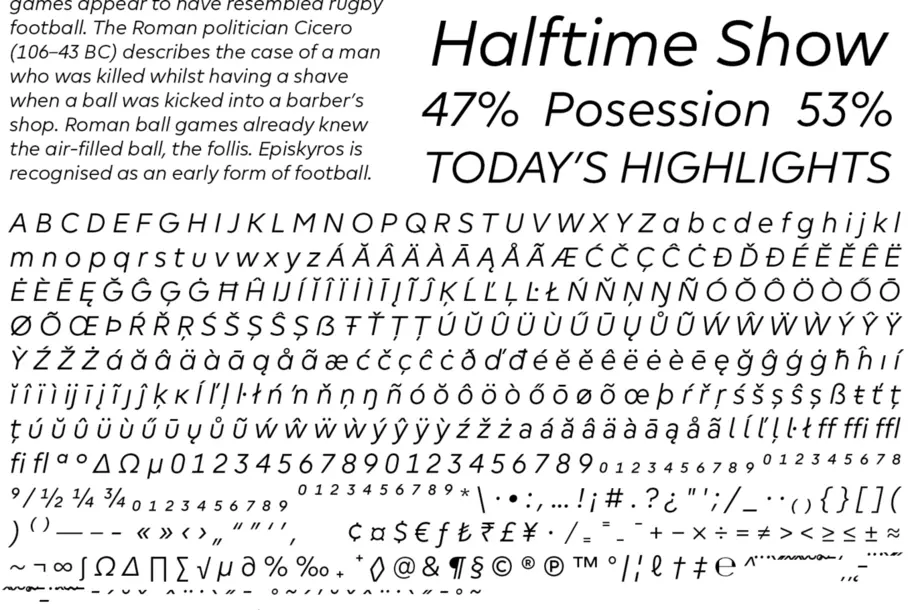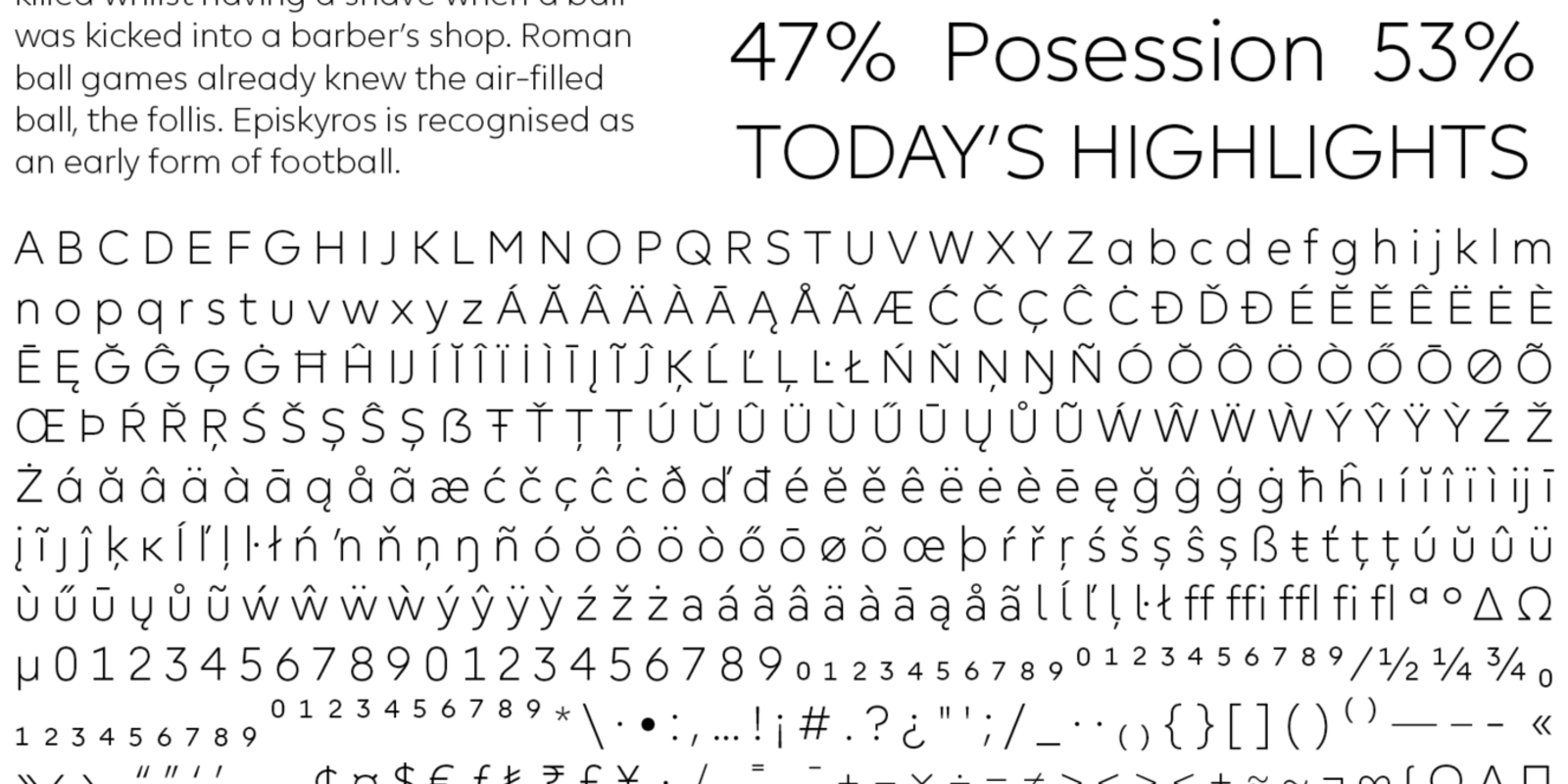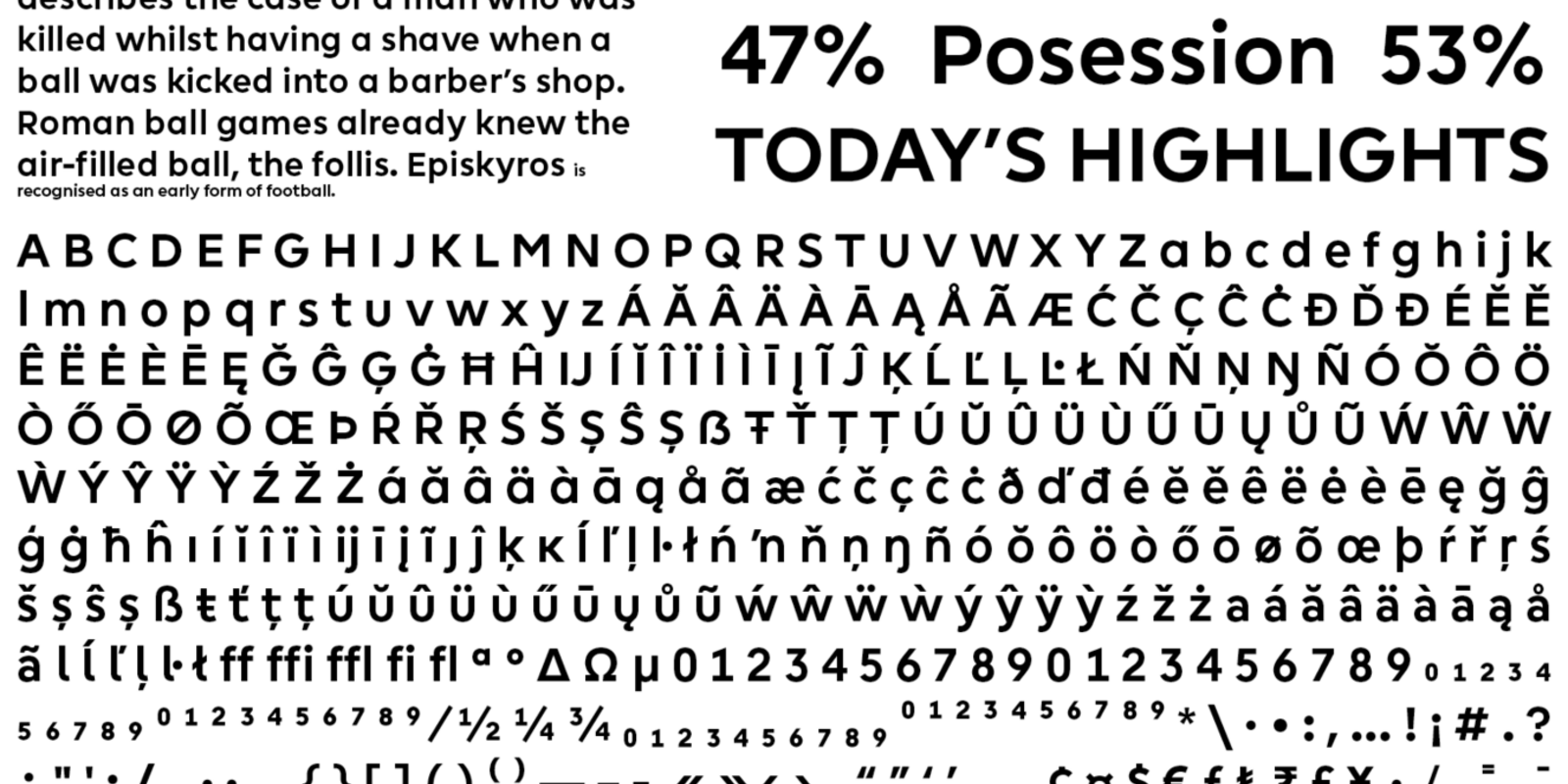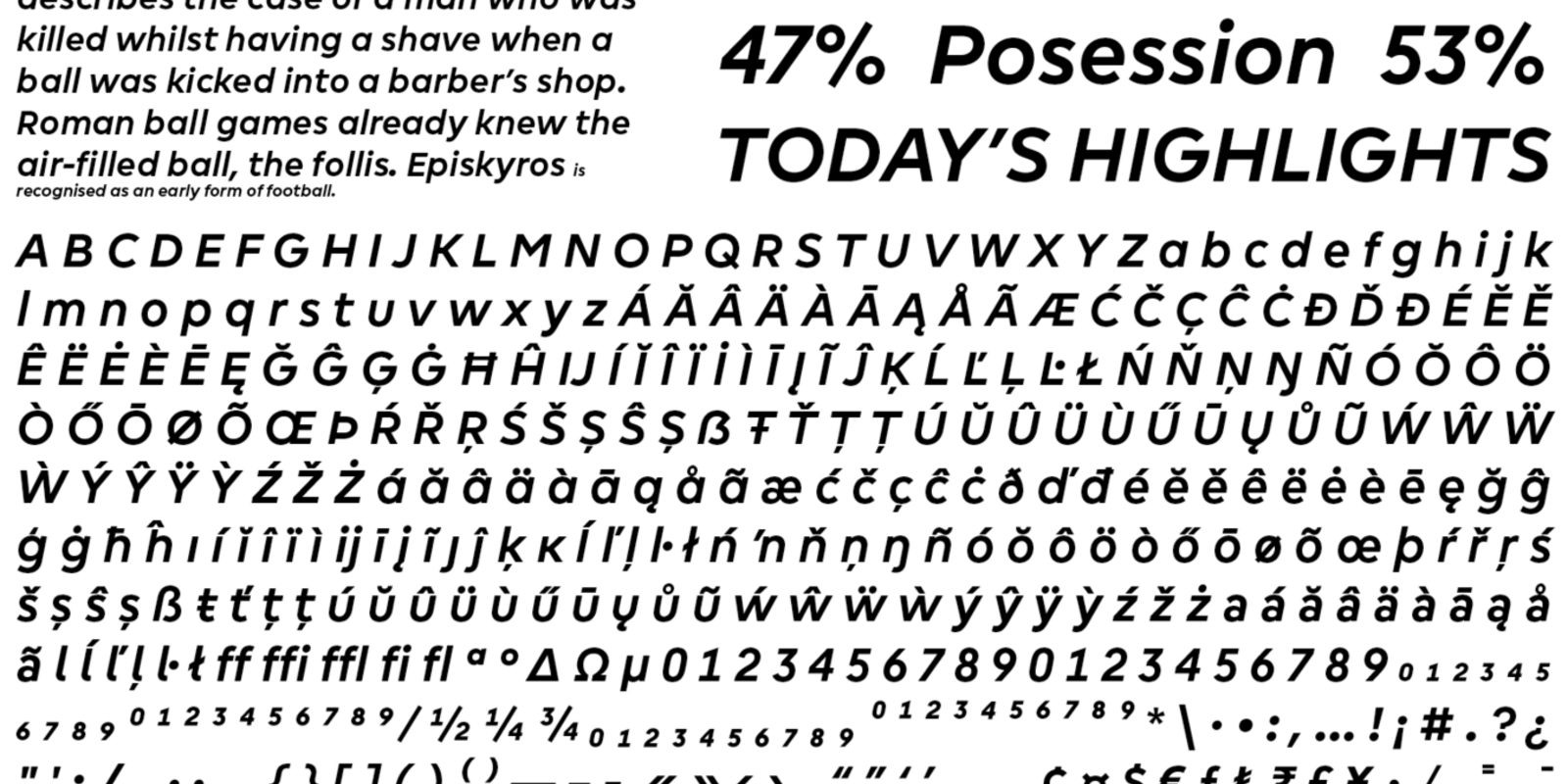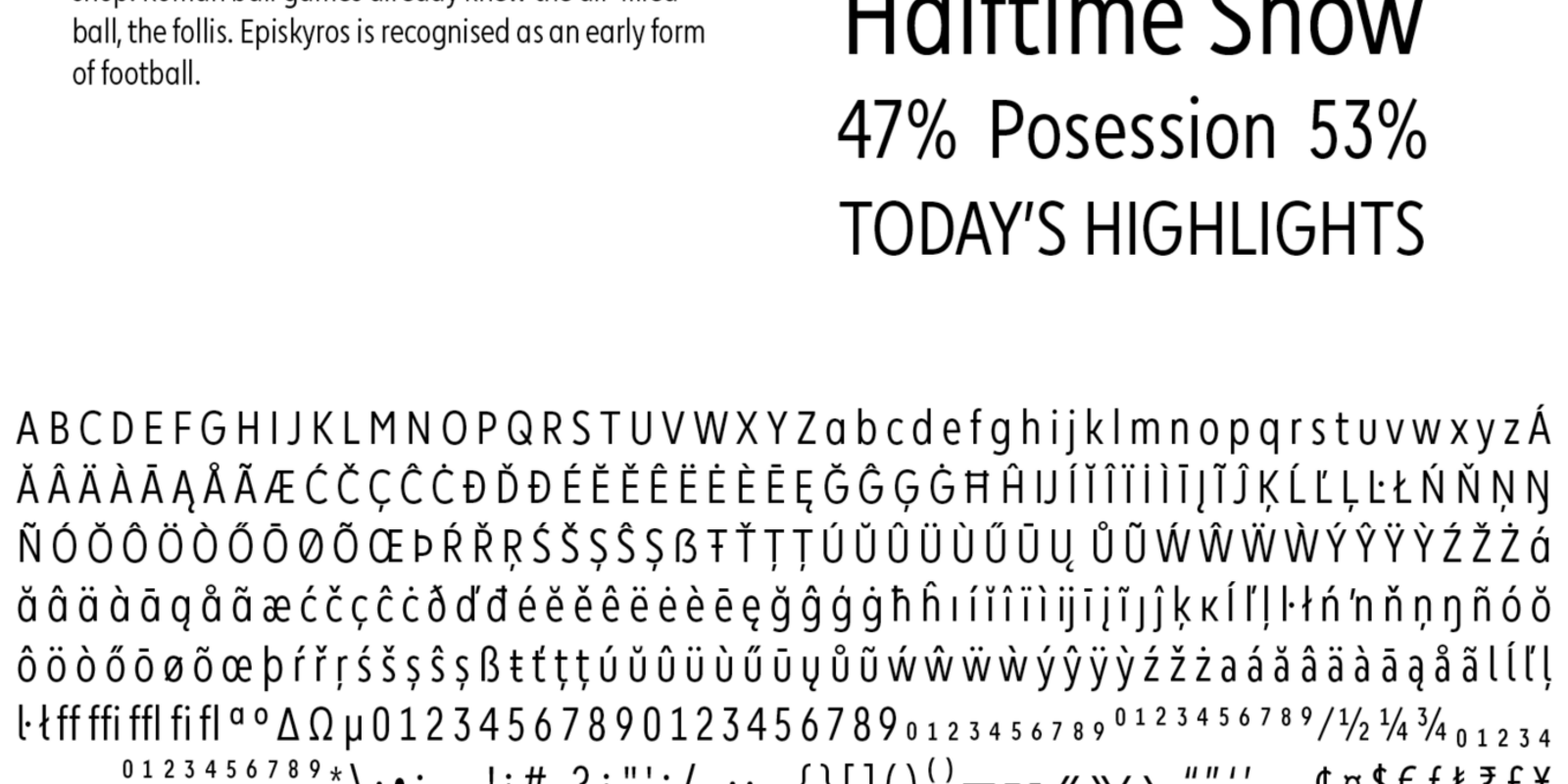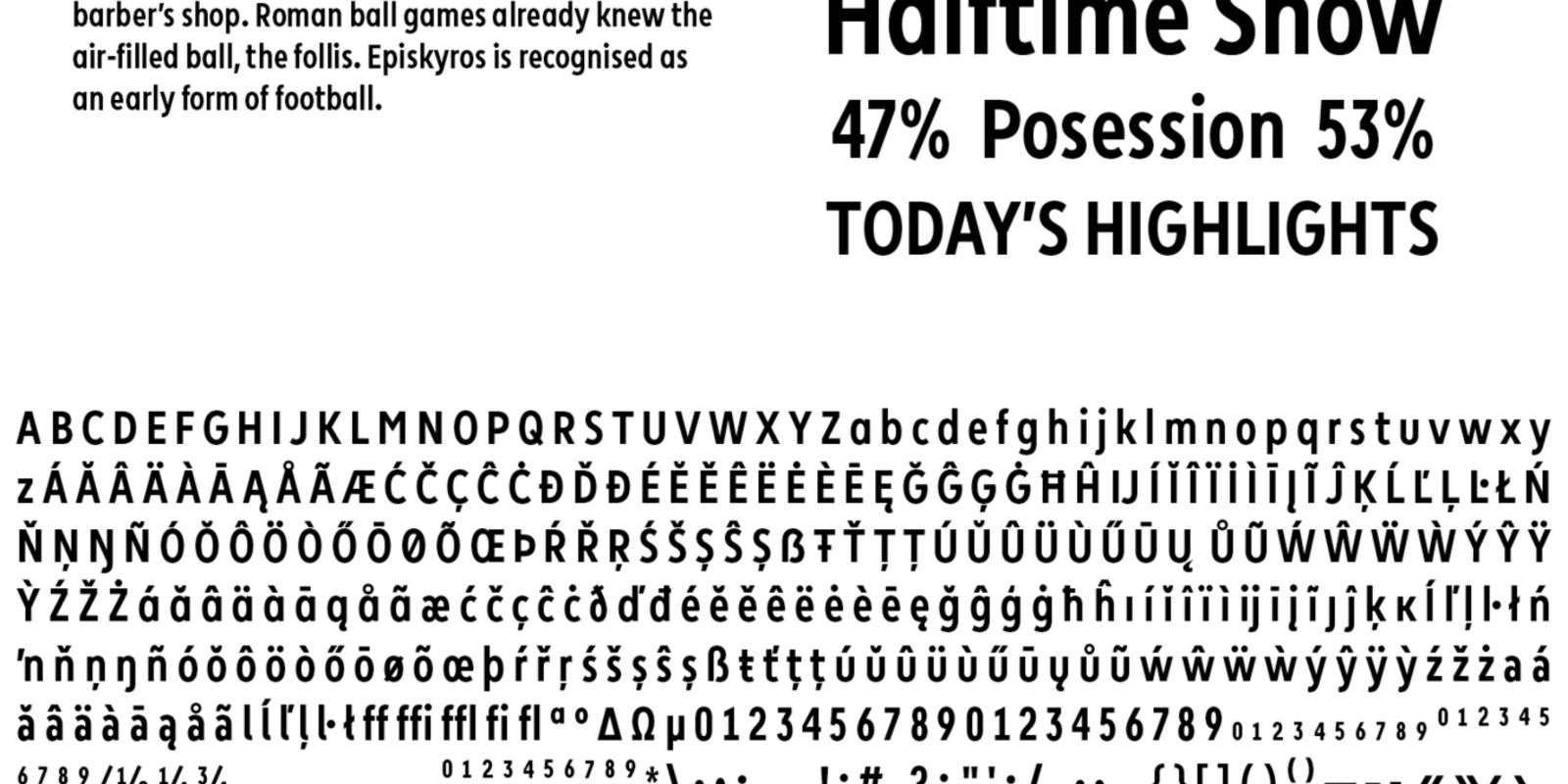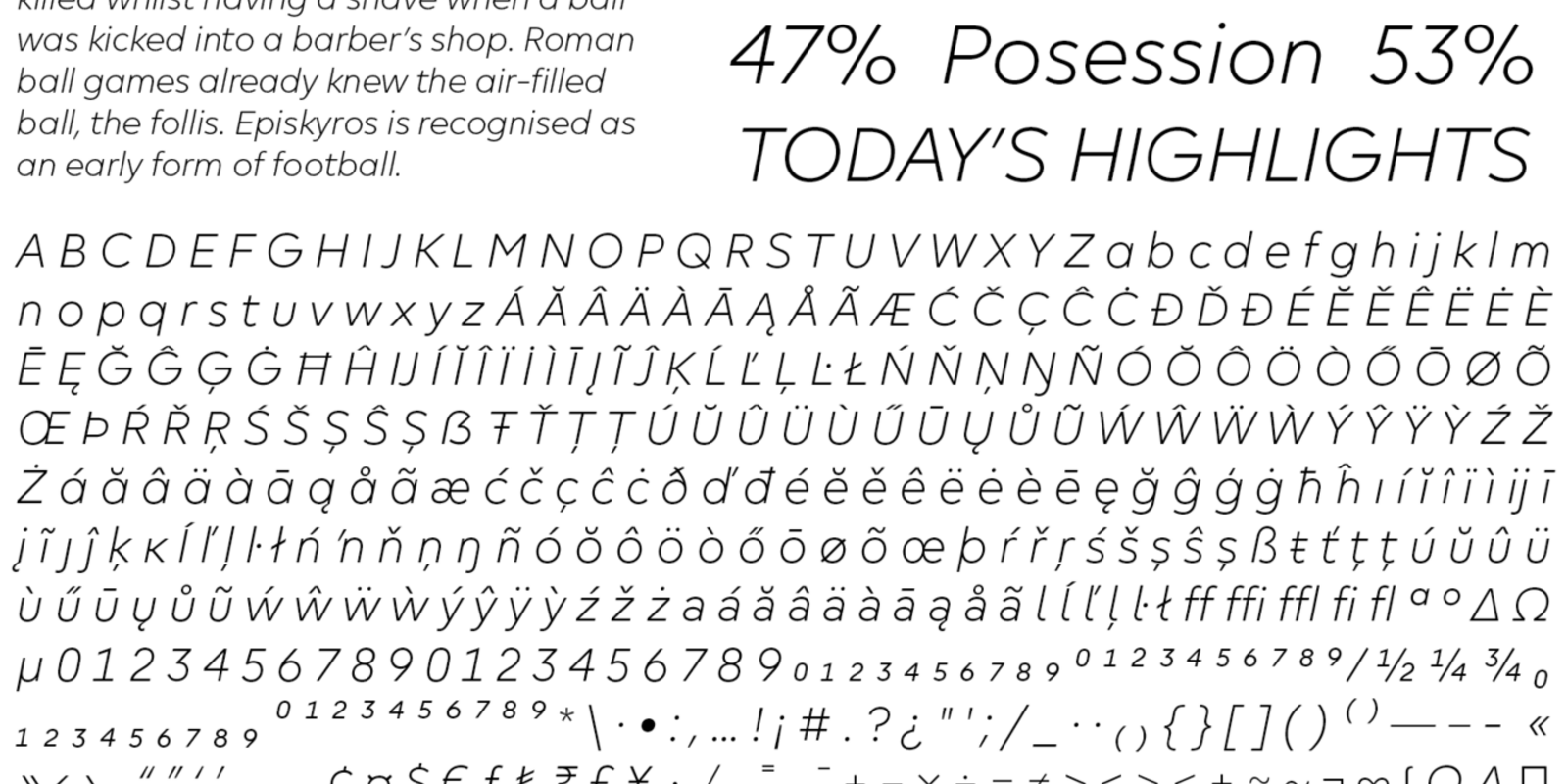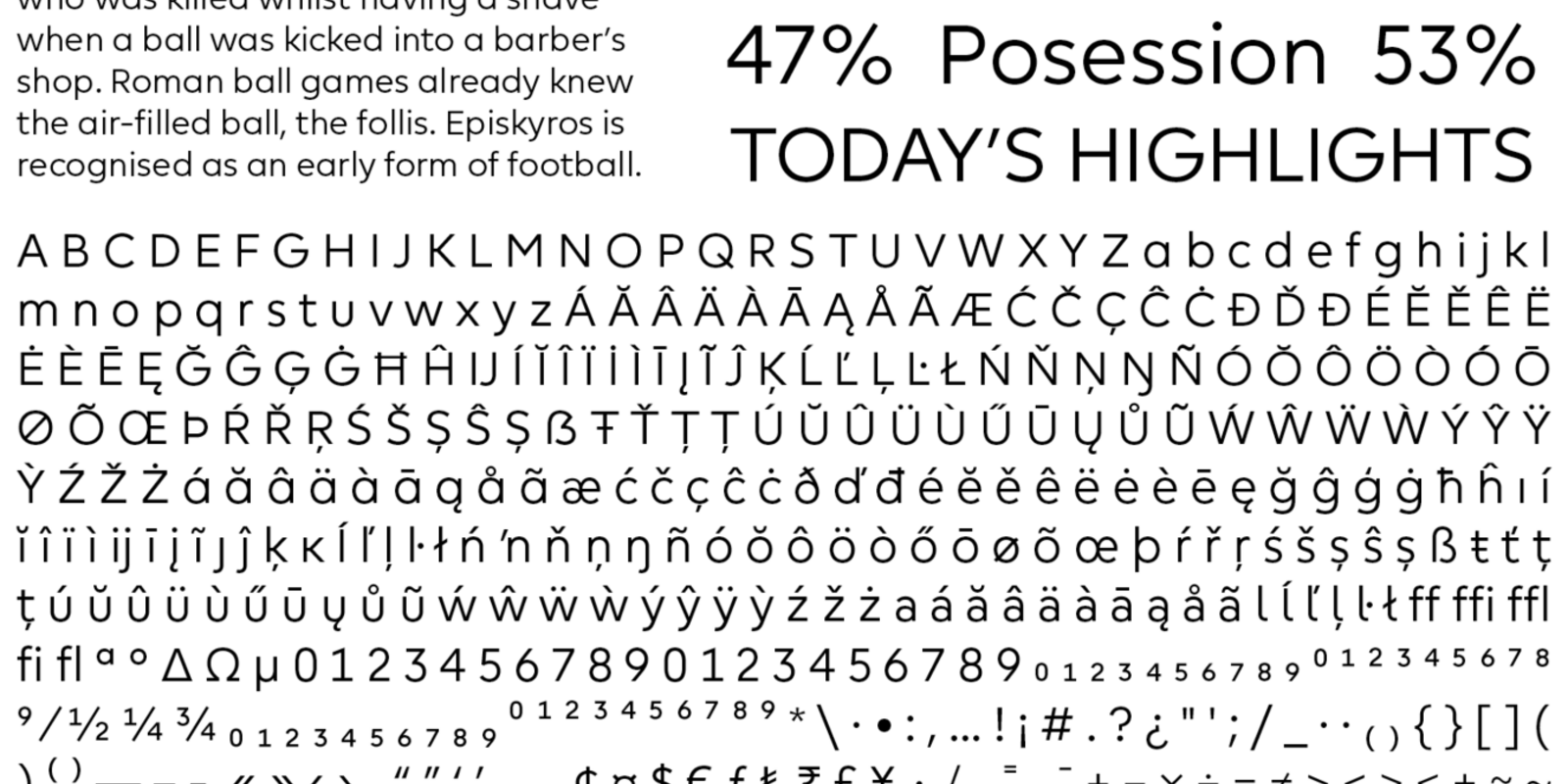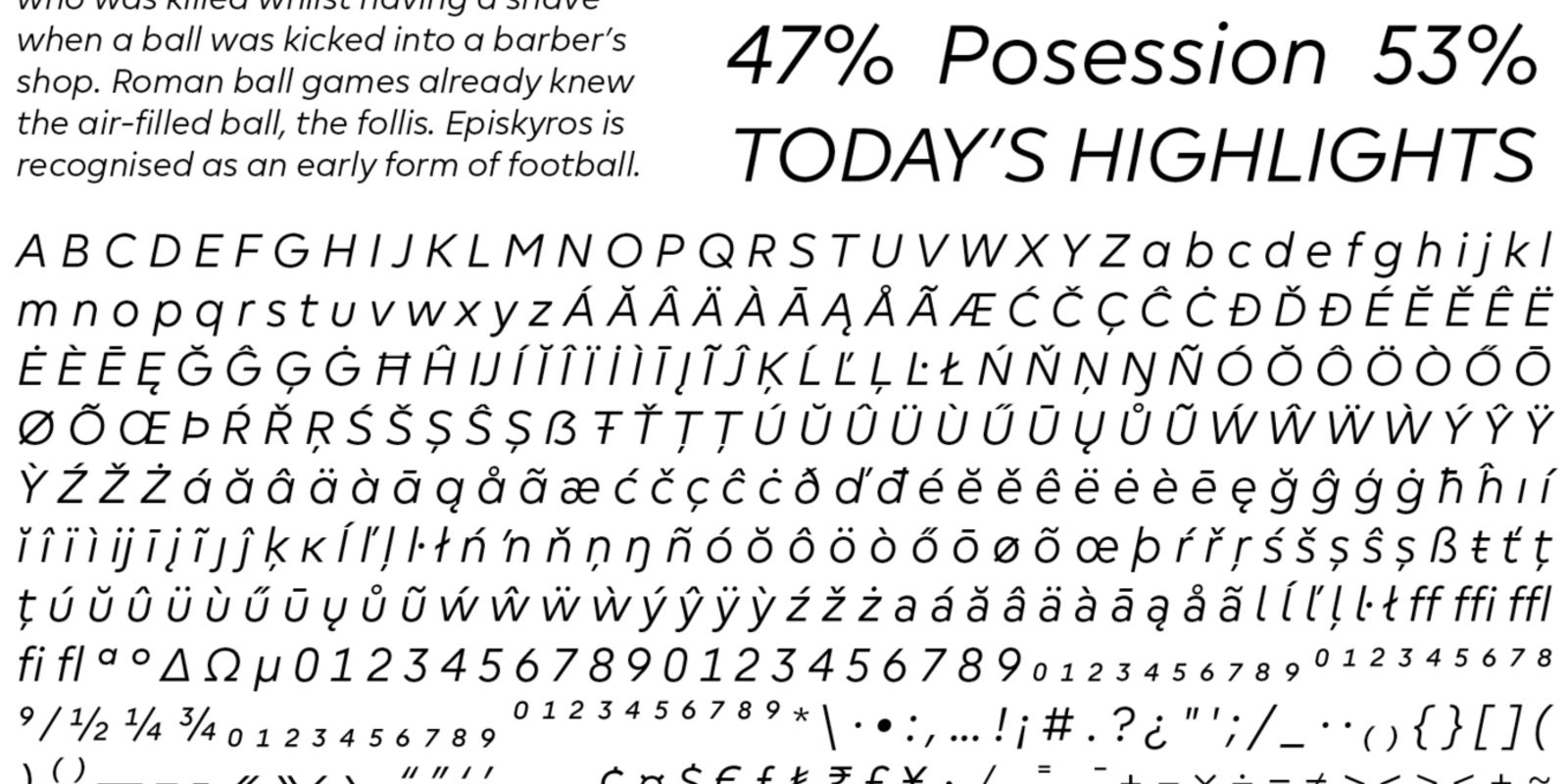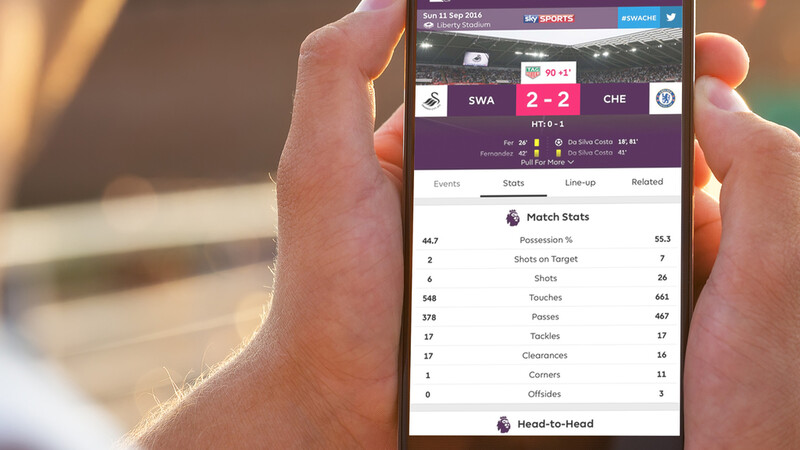
Premier League。
Premier League:よく働き、よく遊ぶブランド.
Monotypeのタイプデザイナーである大曲都市は、DesignStudioと密に連携し、Premier League用にあらゆる場面に対応できるジオメトリック・サンセリフを開発しました。この書体は、スクリーンや選手の背番号、テレビ放送やリーグ表といった多岐にわたるメディアで、確かなパフォーマンスを発揮するようにデザインされています。
「今、人々がサッカーを観ているときに注意を引こうとするのは、スマートフォンやパソコンの中のコンテンツです。私たちが競っている相手は、そういったものなのです」 ”
以前、Premier Leagueはすべて大文字の書体を使っていましたが、より新鮮で親しみやすいトーンと、さまざまなメディアに柔軟に適応できるデザインが求められていました。ヨーロッパのプロサッカーリーグ間での競争がかつてないほど激しくなる中、このリブランディングは、ブランドが視覚的に目立つだけでなく、商業的な実用性においても優れたものにする必要がありました。
「10年前に設計された、デジタル時代を想定していないデザインから脱却することにしました」とDesignStudioのチームは語ります。「ライオンのロゴを描き直し、全体がよりクリーンでシンプルになりました。スケールが大きくてもインパクトを保てる、なおかつデジタル環境でも明瞭に機能する書体が必要でした」
この書体は、大きなサイズで機能するだけでなく、リーグ表で使われるような非常に小さなサイズ、特に名前の長い選手に合わせて字幅を圧縮しても効果的に見える必要がありました。そのため、例えばイングランド代表選手Alex Oxlade-Chamberlainの名前をテストケースとして使用するなど、通常とは異なる書体の検証が行われました。
「大文字だけの太めの書体では、うまくいかないことが明らかになった瞬間でした」とDesignStudioは語ります。「それに対処する仕事は楽しかったですね」
この書体のルーツは、リブランディング初期にDesignStudioが描いたワードマークにあります。小文字の「r、g、m」に見られる、わずかに先細りになったステム(縦線)を手がかりに、大曲はスタジオと密に連携し、それらのディテールを書体ファミリー全体に共通するデザインのDNAとして取り込んでいきました。彼はチームとともにイーストロンドンのオフィスに滞在し、巨大に印刷された文字の上に直接描き込みながら作業を進め、スタジオの提案に応じて調整を加えていきました。
Premier Sansは、テレビ、各種配信、印刷物、Webサイト、アプリ、スタジアム内の掲示といった、目に付くあらゆる場面で活用できる万能さが必要でしたが、それと同時に、ブランドに新たな個性をもたらし、独自性を持って表現できることも重要でした。
「基本的には機能性を重視した書体ですが、そこにさりげなく遊び心を忍ばせました」とスタジオは付け加えます。
「 今、人々がサッカーを観ているときに注意を引こうとするのは、スマートフォンやパソコンの中のコンテンツです。私たちが競っている相手は、そういったものなのです」 ”
「私たちはToshi(大曲)と協力して、より面白い文字を検討し、そこから数字や句読点にまで展開させていきました。長文を読む際のまとまりには影響しないけれど、拡大して見出しレベルの大きさで使われたときに個性が感じられるような要素を探していったのです」
縦画の上部にわずかな角度を加えることで、この書体は他のジオメトリック・サンセリフと一線を画すデザインとなりました。特に数字には重点が置かれ、時計表示やリーグ表、その他の画面上でも明確に見分けられるようにデザインされています。
「テレビやモバイルで多用されることはわかっていたので、数字が明確に識別できることが不可欠でした」と大曲は語ります。
また、この書体はPremier Leagueのブランドイメージを、単なるスポーツ団体にとどまらず、GoogleやAppleといった、ブランディングの最前線を走る企業とも親和性のあるものへと視覚的に引き上げる役割を果たしています。
「私たちが求めていたのは、もっとパーソナルで、開かれた感覚を持つものでした」とDesignStudioは語ります。「これらのブランドと肩を並べ、同じ時代を共有することを意識していたんです」
「今、人々がサッカーを観ているときに注意を引こうとするのは、スマートフォンやパソコンの中のコンテンツです。私たちが競っている相手は、そういったものなのです」